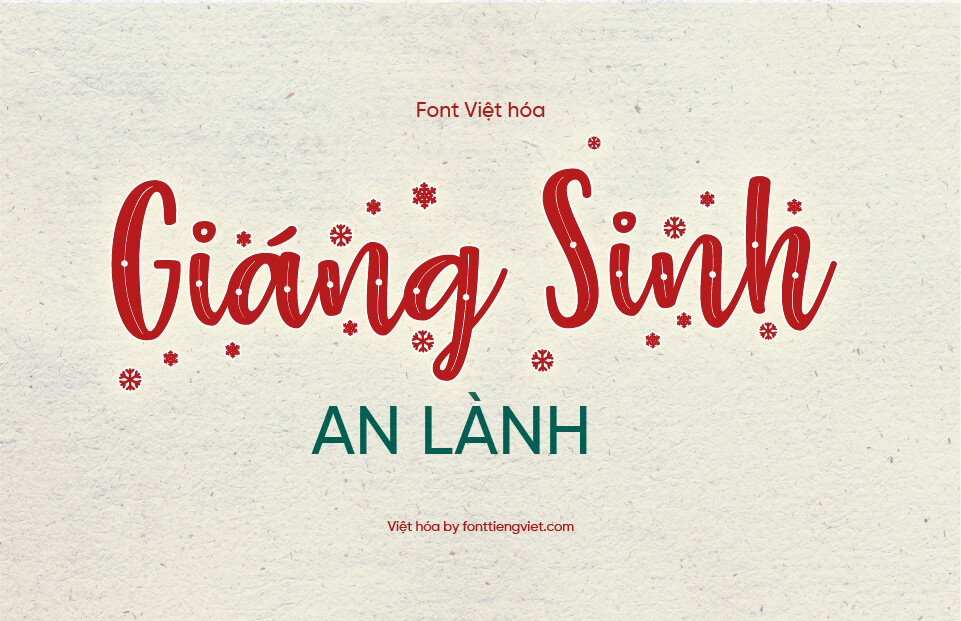
Font Việt hóa 1FTV VIP The Perfect Christmas – Font Giáng Sinh Đẹp, Sang & Dễ Dùng
Font Việt hóa 1FTV VIP The Perfect Christmas – Giáng sinh
Font Việt hóa 1FTV VIP The Perfect Christmas là mẫu font mang không khí Noel rõ nét: ấm áp, vui tươi và nổi bật khi sử dụng trong các thiết kế mùa lễ hội. Nếu bạn đang cần một font “đúng chất Giáng sinh” để làm thiệp chúc mừng, banner khuyến mãi, poster sự kiện, cover Facebook/YouTube, story Instagram hay thiết kế bao bì quà tặng, đây là lựa chọn rất đáng thử.
Vì sao The Perfect Christmas được ưa chuộng dịp Noel?
Điểm mạnh của The Perfect Christmas nằm ở “tính trang trí” và cảm xúc. Font tạo ra cảm giác thân thiện, rộn ràng, phù hợp với các thông điệp như: Merry Christmas, Happy Holidays, Noel Sale, Christmas Party… Khi Việt hóa chuẩn, font sẽ giúp bạn gõ tiếng Việt mượt hơn, giữ nguyên tinh thần thiết kế mà không bị lỗi dấu hay vỡ form chữ.
Ứng dụng thực tế trong thiết kế Font Việt hóa 1FTV VIP The Perfect Christmas
Bạn có thể dùng font này cho nhiều mục đích:
• Thiết kế thiệp Giáng sinh, thiệp mời tiệc Noel, thiệp cảm ơn.
• Làm banner sale cuối năm, poster chương trình ưu đãi.
• Trang trí chữ cho bao bì quà tặng, nhãn dán, tag treo.
• Thiết kế nội dung social: ảnh quote, story, thumbnail video.
Font Việt hóa chuẩn – quan trọng thế nào?
Với các font trang trí, nếu không được Việt hóa kỹ, chữ tiếng Việt dễ gặp lỗi như: dấu tách rời, ký tự không đồng nhất hoặc thiếu glyph. Phiên bản Font Việt hóa 1FTV VIP The Perfect Christmas giúp bạn:
• Gõ tiếng Việt ổn định, hạn chế lỗi dấu.
• Giữ form chữ đẹp khi đưa vào layout.
• Tăng tốc quy trình thiết kế vì không phải “chữa cháy” ký tự.
Gợi ý phối font đẹp cho Noel